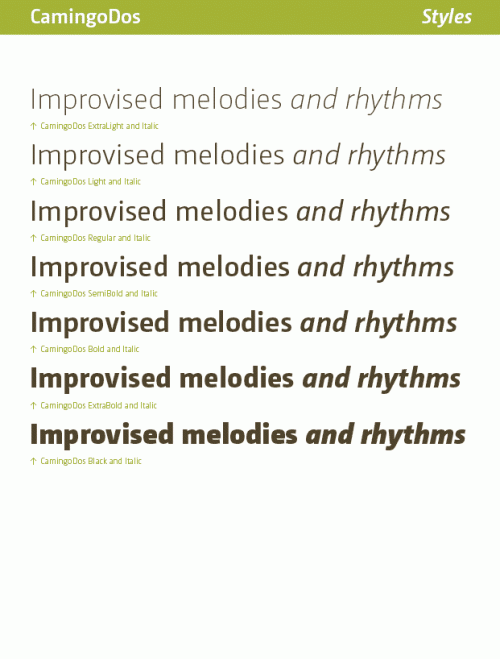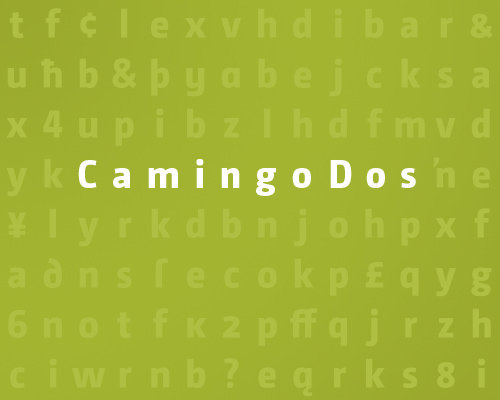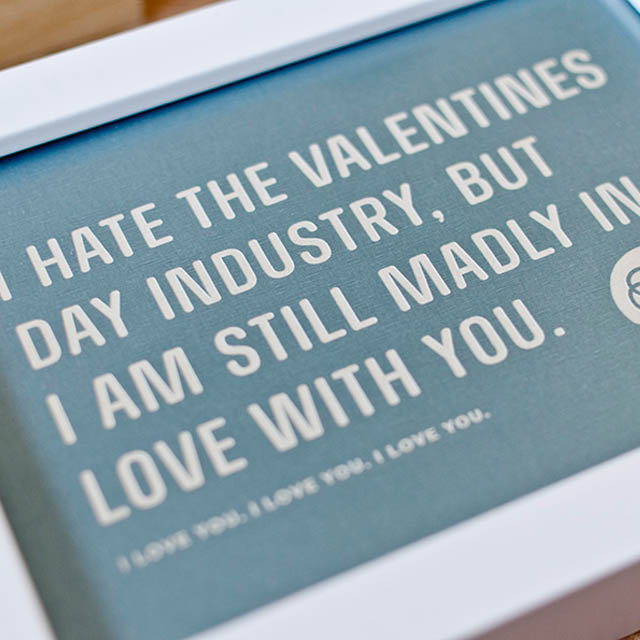
Jan Fromm Kommuniationsdesigner aus Berlin hat vor kurzem eine neue Schriftfamilie CamingoDos veröffentlicht. Genauer gesagt handelt es sich um eine neue Version der Camingo, die bereits seit gut zwei Jahren auf dem Markt ist. Die neue Version enthält einige typografische Verbesserungen, einen vergrößerten Zeichenumfang und wurde um eine SemiCondensed- und Condensed-Variante erweitert.
CamingoDos ist eine Serifenlose Schrift, die vorwiegend für den Einsatz im Editorial und Corporate Design konzipiert ist. Während der Entwicklung standen zwei Aspekte im Vordergrund: Einserseits eine gute Lesbarkeit im Mengensatz, andererseits ein kraftvoller Charakter für Überschriften und Logos.
Die straffen, robusten Formen sorgen für ein einprägsames Auftreten, das besonders in Displaygrößen zum Tragen kommt. Trotzdem sind die Buchstaben offen und klar gezeichnet, wodurch sich die CamingoDos auch für kleine Schriftgrößen eignet. Ein subtiler Kontrast zwischen dicken und dünnen Strichen betont den humanistischen Charakter der Schrift.
Die gesamte Familie umfaßt 42 Schnitte: Sieben Strichstärken, drei Breiten, jeweils in Roman und Kursiv. Die OpenType Pro-Variante enthält Kapitälchen, sechs Ziffernarten, Ligaturen, Alternativbuchstaben und Pfeile.
man sieht deutlich den einfluss von lu(c)as de groot, aber das ist mitnichten ein manko. im gegenteil.